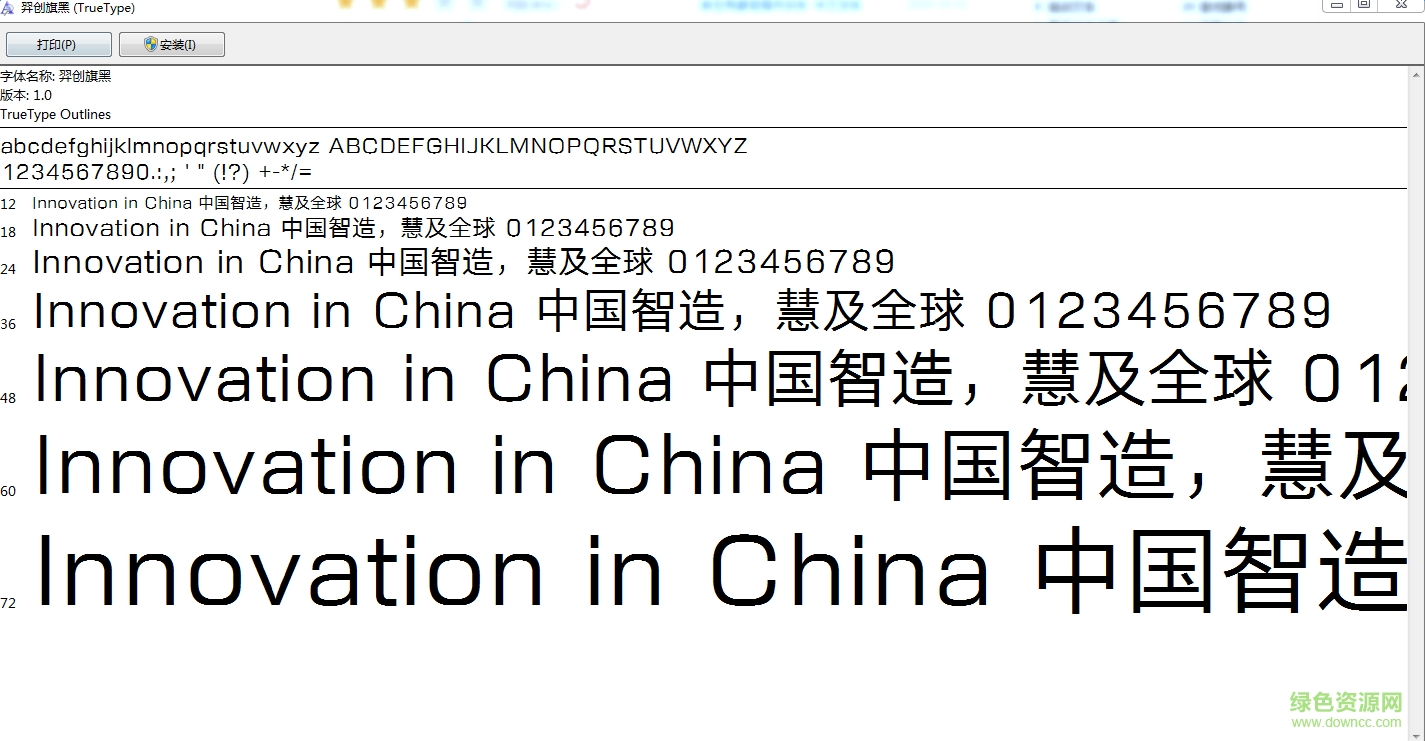
羿創(chuàng)旗黑
羿創(chuàng)旗黑字體是一款略有些小胖的字體,字體圓潤(rùn)好看,可應(yīng)用在影視、印刷、廣告、平面等各個(gè)行業(yè),有需要者歡迎在綠色資源網(wǎng)下載!
羿創(chuàng)旗黑字體介紹
羿創(chuàng)旗黑字體是中文字體庫(kù)中的一款字體,字體端正圓潤(rùn),字體橫折都十分工整,整體上結(jié)構(gòu)十分出眾,而且拐角處還非常有特點(diǎn),喜歡或需要此字體的朋友們可以前來(lái)下載使用。